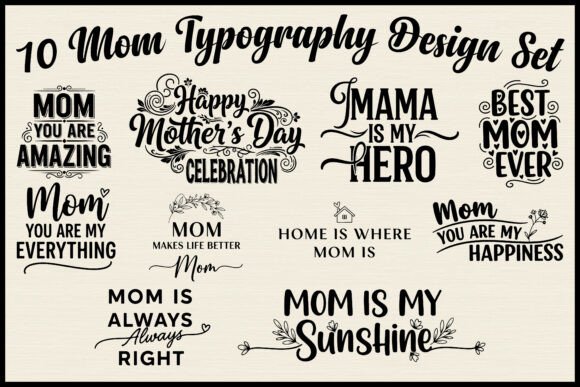
10 Mom Typography Quote SVG Bundle
Si buscas recursos de alta calidad como 10 Mom Typography Quote SVG Bundle, este paquete premium es una opción fantástica para tus proyectos creativos.
Elaborado con precisión, 10 Mom Typography Quote SVG Bundle proporciona vectores limpios, tipografía suave y una licencia comercial para tu tranquilidad.